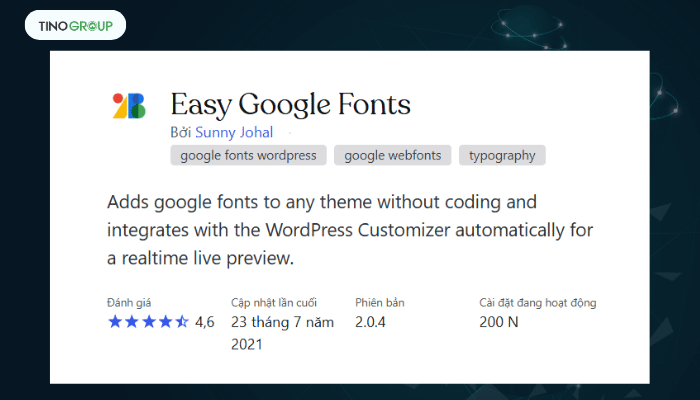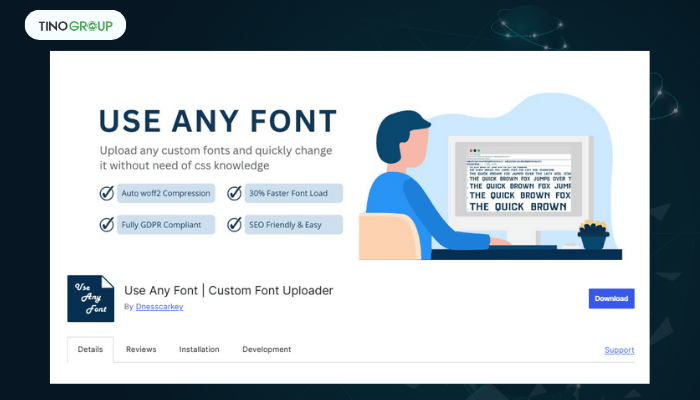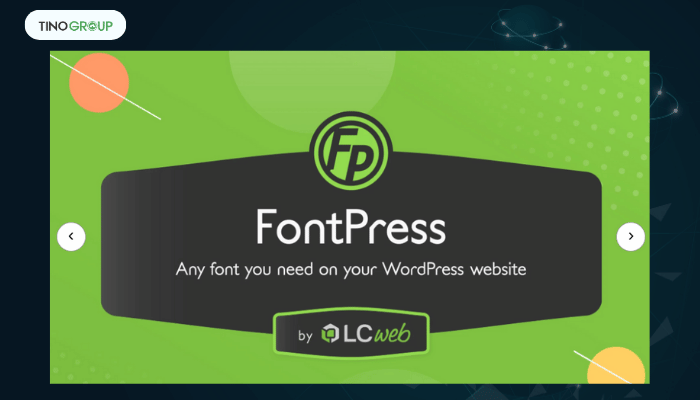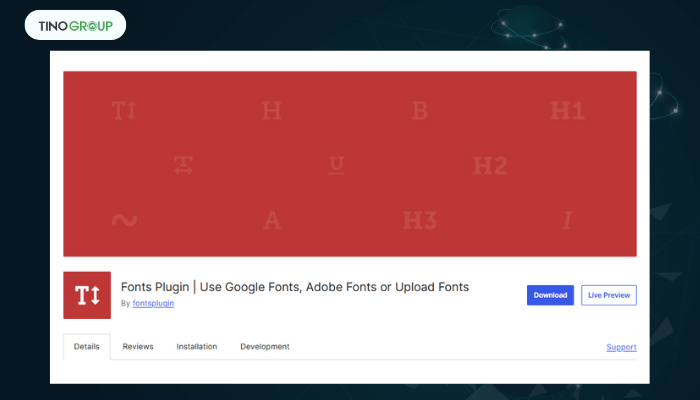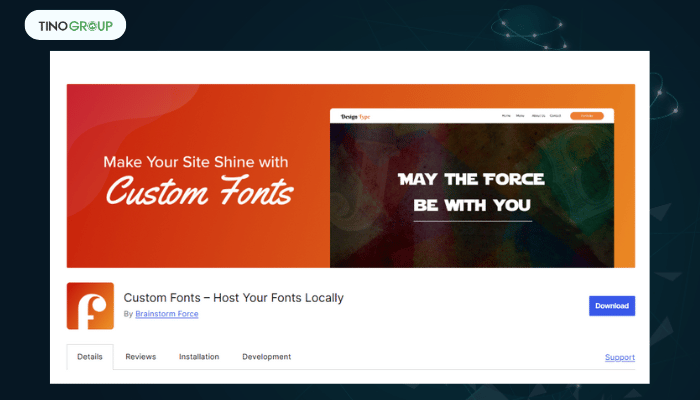
Top 10 plugin font chữ cho WordPress 2026: đẹp, nhẹ, dễ dùng!
Font chữ đóng vai trò quan trọng trong việc tạo nên trải nghiệm người dùng trên website. Một font chữ đẹp không chỉ giúp tăng tính thẩm mỹ mà còn cải thiện khả năng đọc và giữ chân khách truy cập lâu hơn. Bài viết này sẽ giới thiệu top 10 plugin font chữ cho WordPress giúp bạn dễ dàng thay đổi và quản lý font chữ một cách chuyên nghiệp.
Tầm quan trọng của font chữ đối với UX/UI và SEO trong WordPress
Cải thiện khả năng đọc
Một font chữ phù hợp không chỉ giúp website trở nên chuyên nghiệp hơn mà còn nâng cao khả năng đọc hiểu nội dung. Khi font chữ rõ ràng, dễ nhìn, người dùng sẽ tiếp cận thông tin nhanh chóng, giảm cảm giác mệt mỏi khi đọc và tăng khả năng tương tác với nội dung. Điều này đặc biệt quan trọng với các website tin tức, blog hay thương mại điện tử, nơi mà trải nghiệm đọc ảnh hưởng trực tiếp đến quyết định của người dùng.
Tầm quan trọng của font chữ đối với UX/UI và SEO trong WordPress
Giảm tỷ lệ thoát trang
Nếu văn bản khó đọc do font chữ quá nhỏ, khoảng cách chữ không hợp lý hoặc kiểu chữ quá cầu kỳ, người dùng có thể nhanh chóng rời khỏi trang. Ngược lại, font chữ dễ đọc sẽ giúp nội dung trở nên hấp dẫn hơn, tăng thời gian ở lại trang và giảm tỷ lệ thoát.
Ngoài ra, font chữ còn có thể tác động đến cảm xúc người dùng. Các font Serif như Times New Roman tạo cảm giác trang trọng và chuyên nghiệp, trong khi font Sans-serif như Open Sans lại mang đến sự hiện đại và thân thiện. Với các website sáng tạo, font Script hoặc font nghệ thuật có thể giúp truyền tải cá tính thương hiệu hiệu quả hơn.
Tối ưu trải nghiệm trên thiết bị di động
Font chữ phù hợp còn giúp tối ưu trải nghiệm trên thiết bị di động. Với ngày càng nhiều người truy cập web bằng điện thoại, việc sử dụng font chữ dễ đọc, có kích thước linh hoạt và hiển thị tốt trên mọi thiết bị là điều cần thiết để nâng cao trải nghiệm người dùng.
Ảnh hưởng đến tốc độ tải trang
Một số font chữ tùy chỉnh hoặc quá nhiều font có thể làm chậm trang web, ảnh hưởng đến hiệu suất và trải nghiệm người dùng. Google đánh giá cao những website có tốc độ tải nhanh, vì vậy sử dụng các font chữ được tối ưu hóa, chẳng hạn như Google Fonts, là một lựa chọn hợp lý để đảm bảo hiệu suất tốt mà không làm ảnh hưởng đến thiết kế.
Giúp Google trong việc hiểu và lập chỉ mục nội dung của website
Các tiêu đề (H1, H2, H3…) cần sử dụng font chữ dễ đọc để nhấn mạnh nội dung quan trọng, giúp công cụ tìm kiếm nhận diện nhanh cấu trúc trang. Do đó, lựa chọn font chữ không chỉ là vấn đề thẩm mỹ mà còn có tác động trực tiếp đến thứ hạng tìm kiếm của website.
Tiêu chí chọn plugin font chữ cho website WordPress
Dễ sử dụng
Một plugin font chữ tốt cần có giao diện trực quan, dễ cài đặt và thiết lập, ngay cả với những người không có nhiều kinh nghiệm về WordPress. Plugin nên cung cấp tùy chọn thay đổi font chữ nhanh chóng trong phần tùy chỉnh (Customizer) hoặc thông qua giao diện đơn giản trong bảng điều khiển WordPress. Ngoài ra, khả năng xem trước font chữ trước khi áp dụng cũng là một tính năng quan trọng giúp người dùng dễ dàng chọn lựa font phù hợp với thiết kế website.
Hỗ trợ nhiều font chữ
Một plugin tốt nên hỗ trợ đa dạng font chữ, bao gồm cả Google Fonts và Custom Fonts. Google Fonts là thư viện font miễn phí phổ biến, được tối ưu hóa cho web và dễ dàng tích hợp vào WordPress. Trong khi đó, Custom Fonts giúp bạn tải lên và sử dụng những bộ font riêng biệt, giúp website có phong cách độc đáo và nhất quán với thương hiệu. Một số plugin cao cấp còn hỗ trợ Typekit (Adobe Fonts) hoặc tích hợp với các thư viện font bên thứ ba, mang lại sự linh hoạt cao hơn trong việc lựa chọn kiểu chữ.
Tiêu chí chọn plugin font chữ cho website WordPress
Khả năng tương thích với theme và page builder
Không phải tất cả các plugin font chữ đều hoạt động tốt với mọi theme hoặc page builder. Do đó, trước khi cài đặt, bạn cần kiểm tra xem plugin có tương thích với theme WordPress mà bạn đang sử dụng hay không. Ngoài ra, nếu bạn sử dụng các page builder như Elementor, WPBakery, Divi, Beaver Builder, hãy đảm bảo plugin có thể hoạt động mượt mà với các công cụ này để tránh xung đột hoặc lỗi hiển thị.